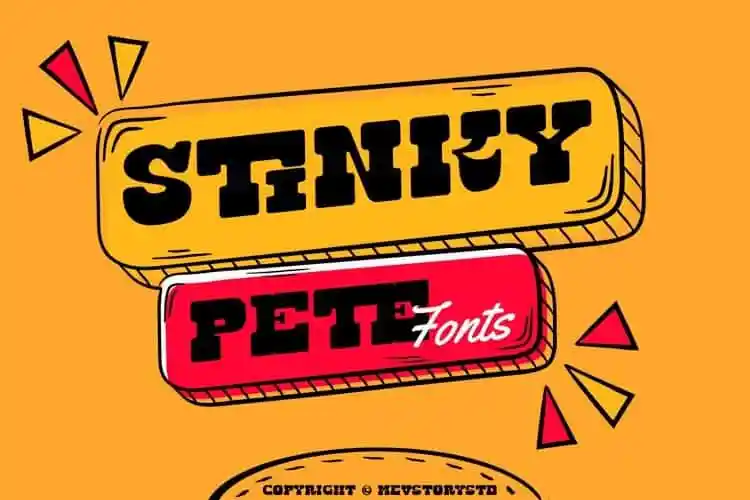
Stinky Pete Display Font – Download Grátis
A Stinky Pete Display Font é uma opção moderna e vibrante para quem busca imprimir seus projetos com estilo. Esta fonte foi criada especificamente para utilização em elementos visuais chamativos, como cabeçalhos, mas também se adapta bem a textos menores e parágrafos em um número variado de aplicações gráficas. Seja para criar identidades visuais memoráveis (como logotipos ou cartões de convite), artesanato (como t-shirts ou material de moda), criação de produtos (como embalagens ou materiais promocionais) ou até mesmo para imprimir materiais publicitários como cartazes, jornais e cartas de cumprimento. A Stinky Pete traz características únicas disponíveis em versões abertas, que permitem maior flexibilidade na edição do texto. Isso significa que você pode explorar diferentes estilos e formatos em seus projetos. A fonte está suportada por diversos programas de design da Adobe, como Indesign, Illustrator e Photoshop, facilitando seu uso em qualquer projeto digital ou impresso.